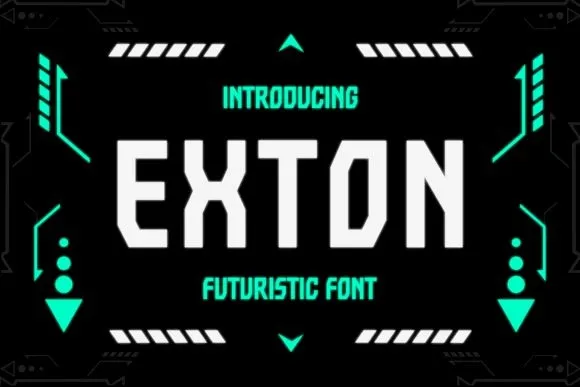
Exton Font – Fonte Grátis
Exton Font
A Exton Font é uma opção visual vibrante e icônica para designers e criativos que buscam uma fonte pixelada poderosa e futurista. Ela possui um estilo robotizado, forjando um caráter poderoso e robusto perfeito para qualquer tipo de design em destaque ou painel de displays. Perfeita tanto para a criação de logotipos quanto para elementos de selos e embalagens, ela também se adapta perfeitamente ao design de capas de revistas, cartazes e até mesmo aos headlines e orelhas dos posters. Seja você um designer profissional ou iniciante, essa fonte pixelada é uma escolha inteligente para quando precisar de um visual chamativo e inovador que destaca sua mensagem.